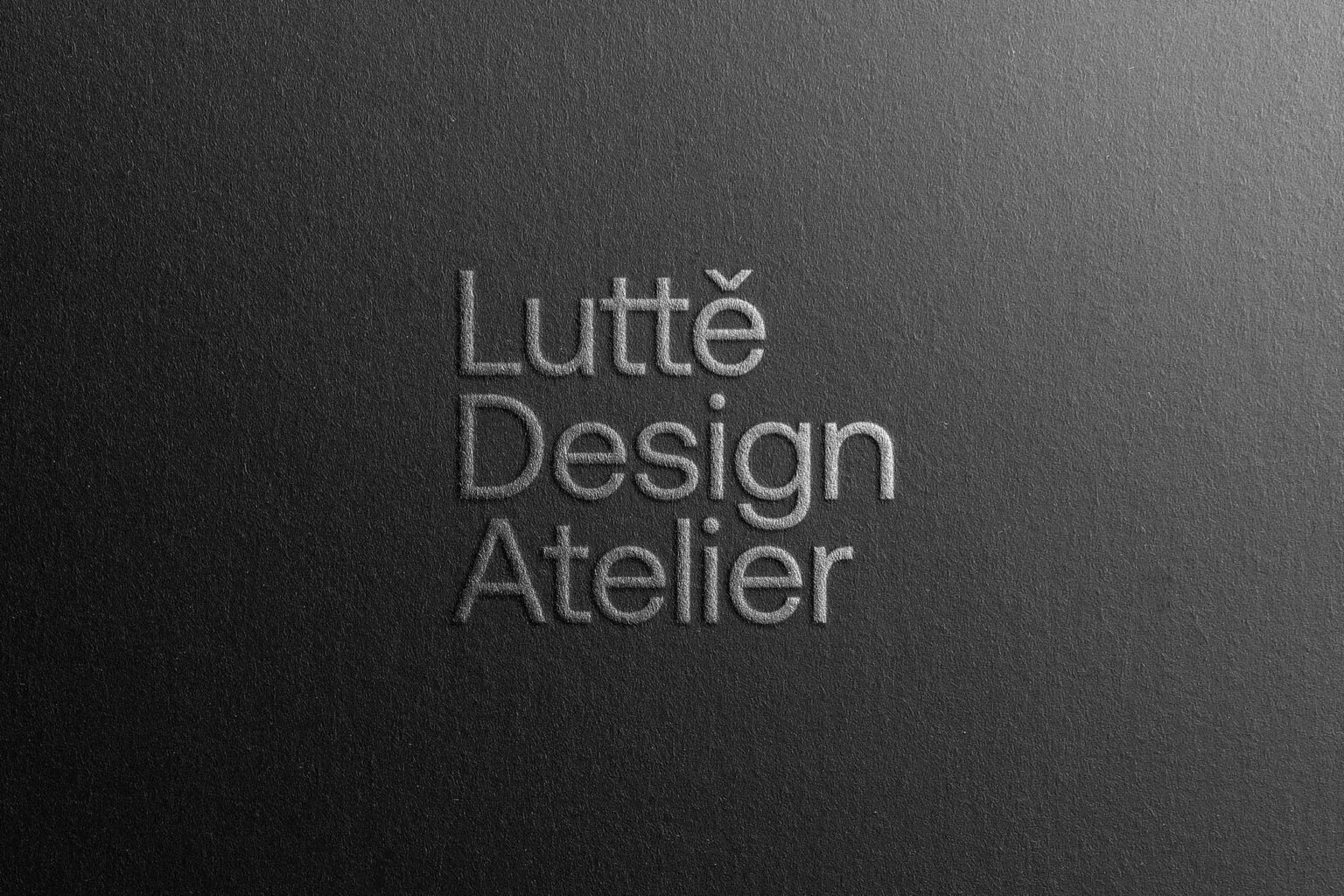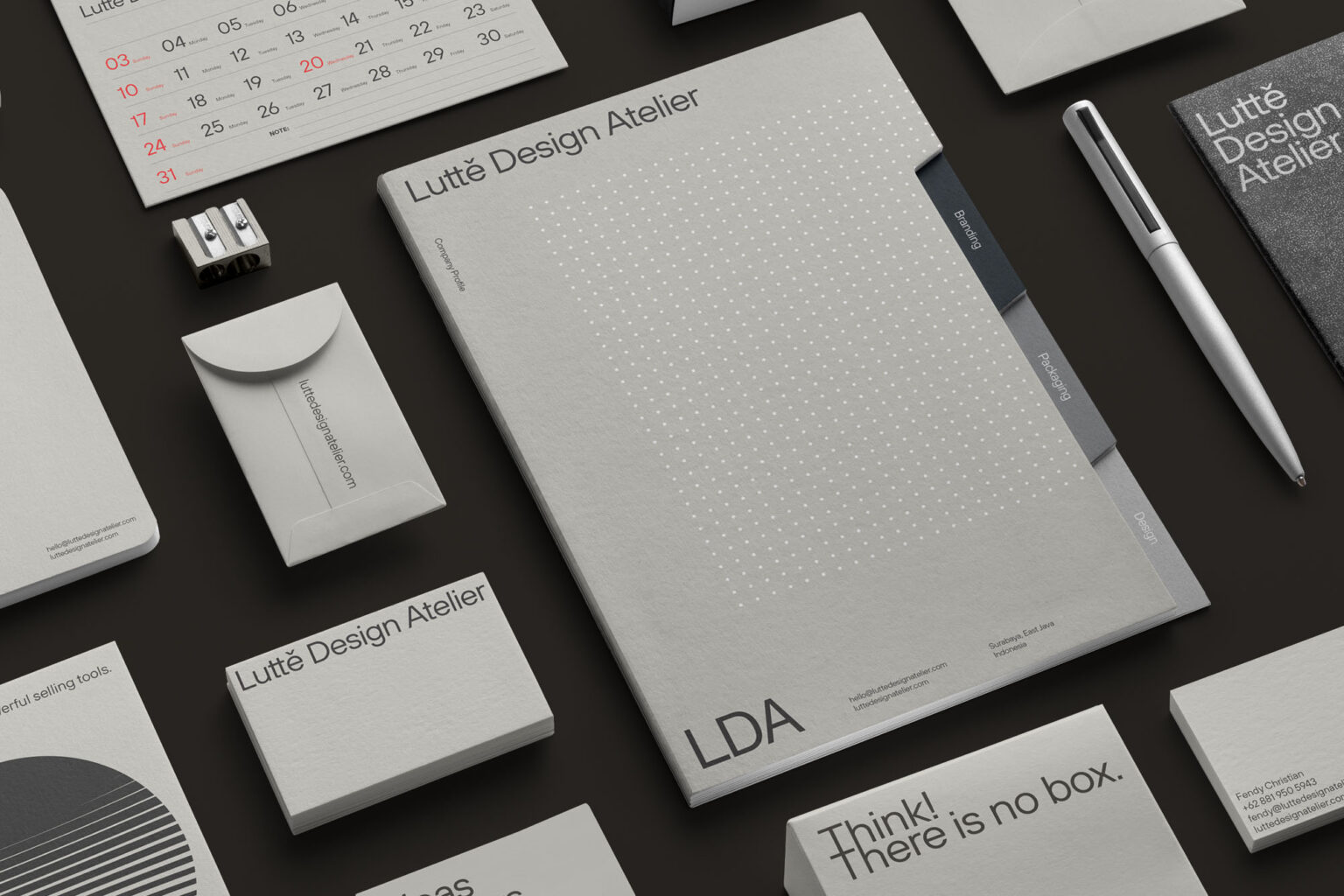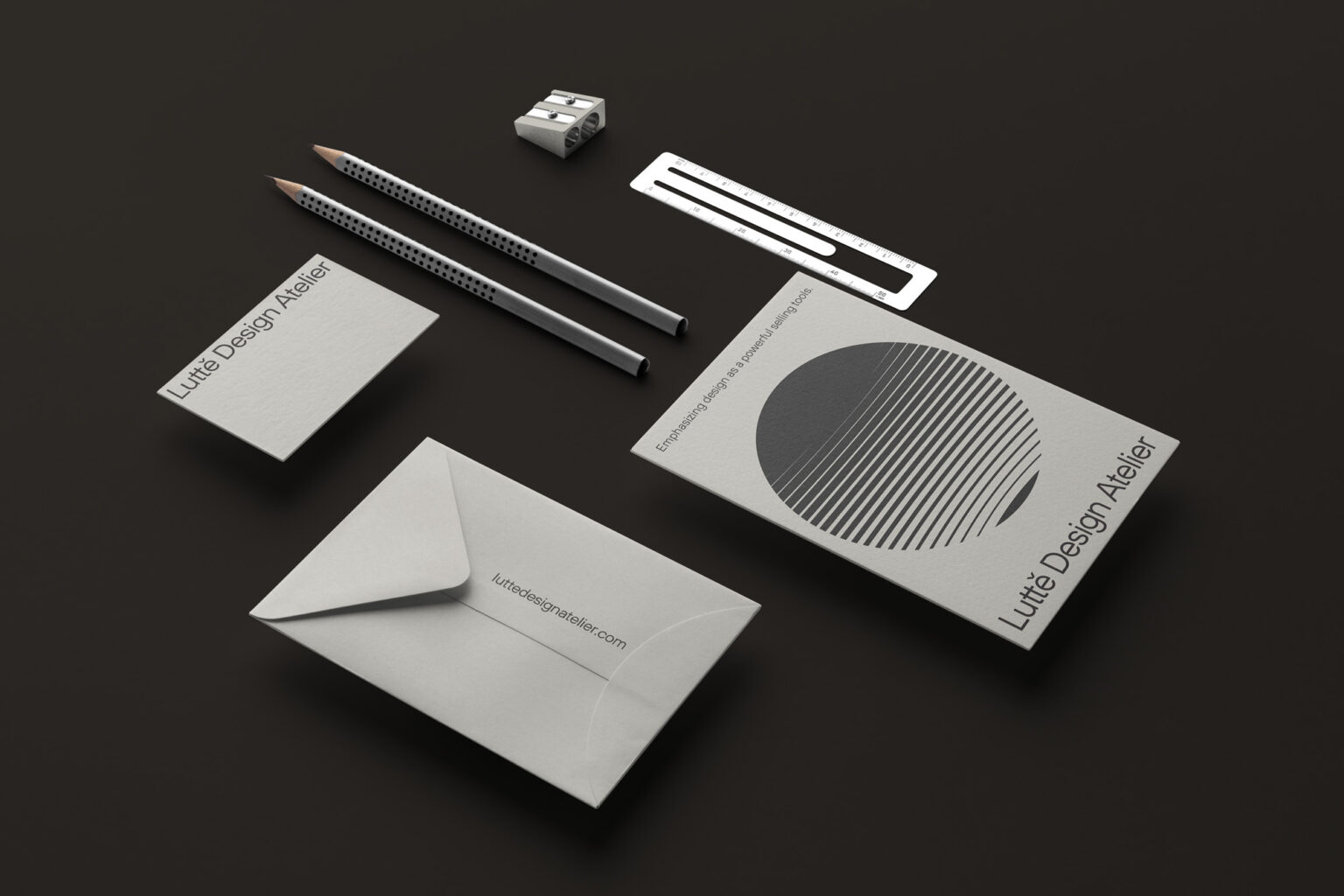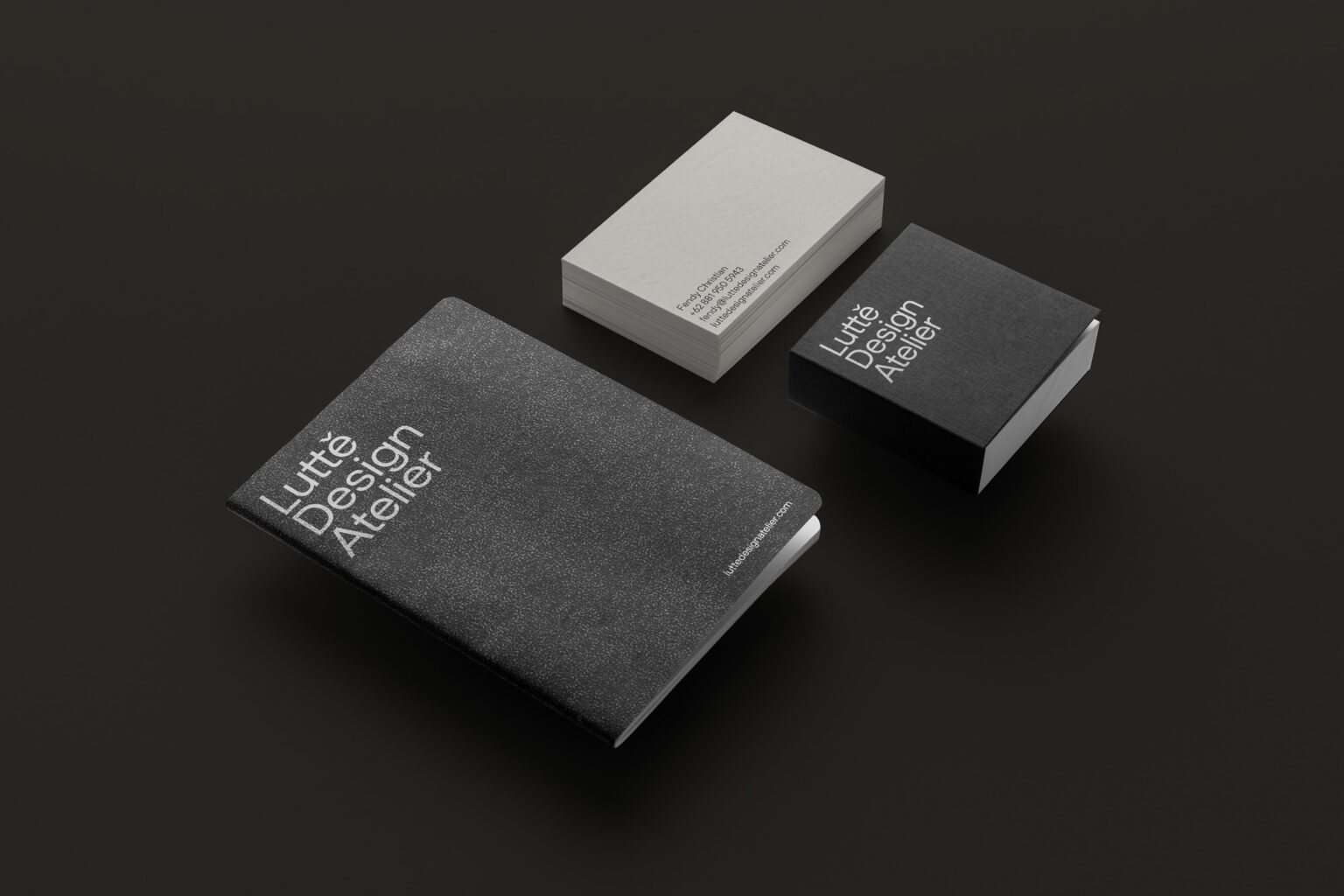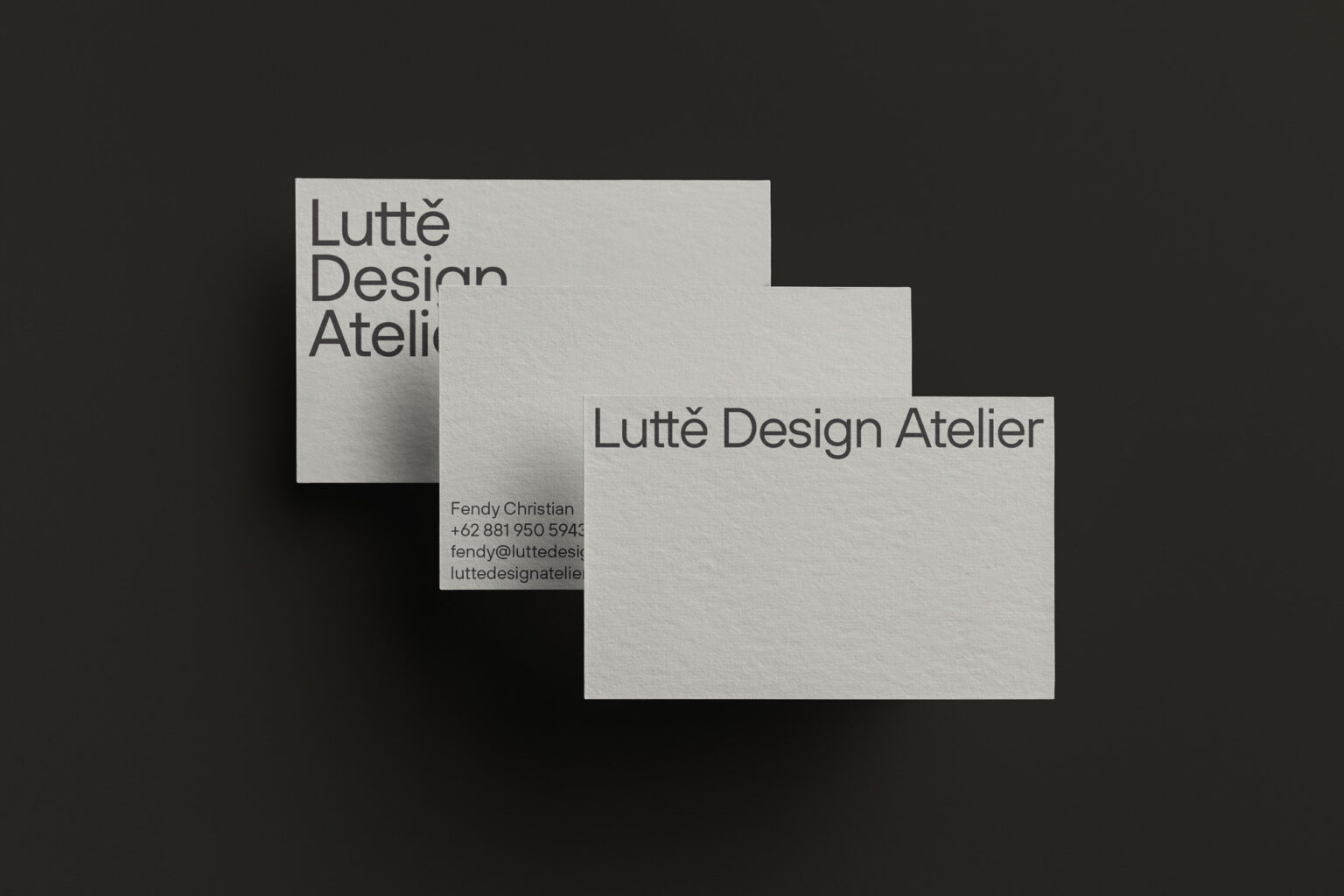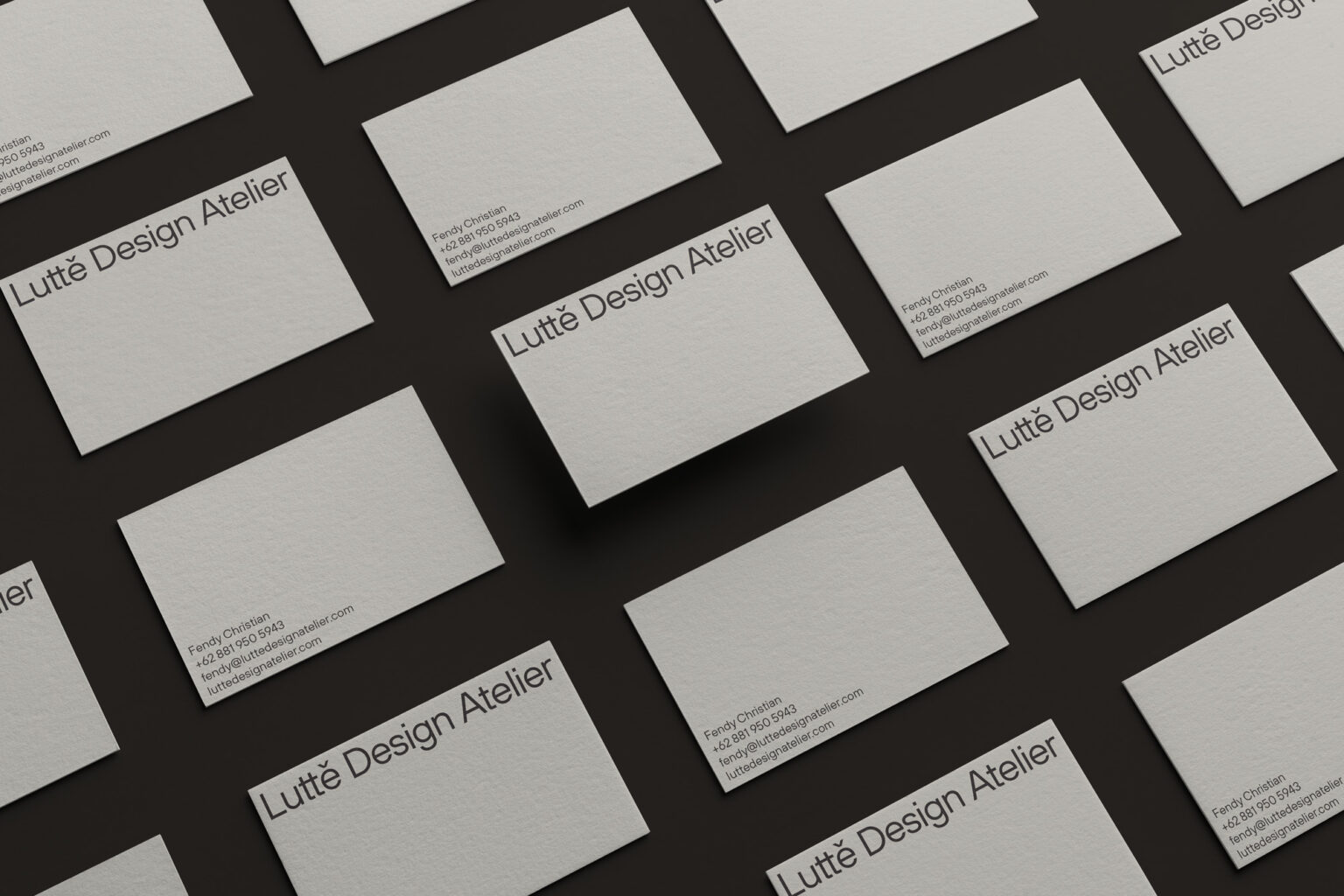
WIDARTO IMPACT ist ein unabhängiges Branding- und Designunternehmen, das den Agenturnamen LUTTE für Lutte Design Atelier kreierte, was so viel bedeutet wie „Überleben/Kämpfen“. Neben der Namensgebung für die Agentur entwarf WIDARTO IMPACT auch die Identität von Lutte, die elegant, supereinfach, ästhetisch ansprechend und anders als die anderer lokaler Agenturen sein sollte. Als Logo für Lutte wurde die Schriftart TT Hoves ausgewählt. TT Hoves ist sehr einzigartig und dennoch einfach.